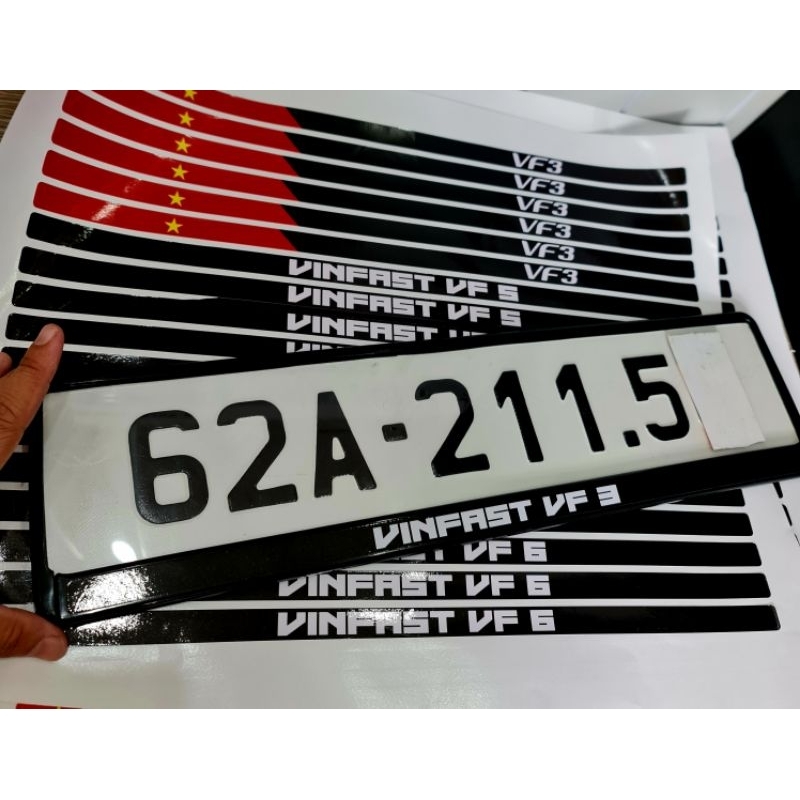
Tạo nên sự khác biệt với Font chữ Vinfast
- Font chữ Vinfast chữ viết tay
- Font chữ Vinfast sáng tạo
- Font chữ Vinfast chuyên nghiệp
- Font chữ Vinfast hiện đại
- Font chữ Vinfast cổ điển
- Font chữ Vinfast trang trí